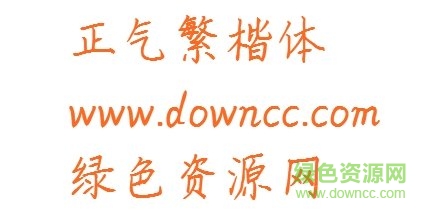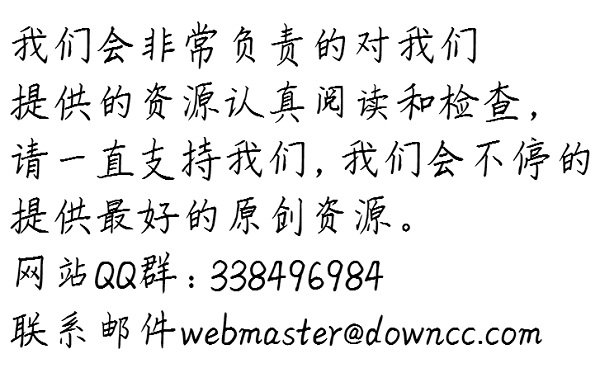
正氣簡繁楷體
正氣繁楷體是一款美化過后的小寶手寫字體,較原字體使用性更為廣泛,支持繁簡體輸入,給字體更加獨特的視覺呈現(xiàn),綠色資源網(wǎng)今日推薦!
正氣繁簡楷體字體介紹
正氣繁楷體是在小寶手寫簡楷體范本的基礎(chǔ)上,應(yīng)廣大字體迷的要求增加了繁體支持,并重寫優(yōu)化了部分簡體字,本字體是簡繁合體版本。
小寶手寫簡楷體專注于簡體輸入,而正氣繁楷體在簡體的基礎(chǔ)上補充了繁體字庫,讓漢字輸入更加高效,可以使用在更多的平面設(shè)計場合了!